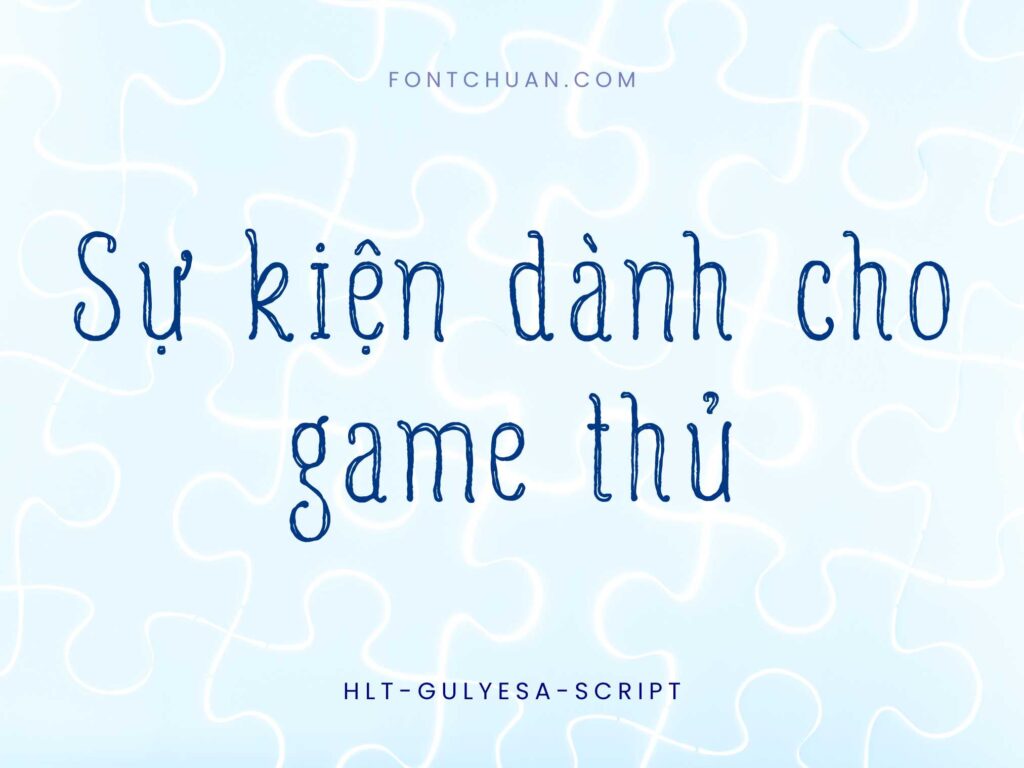
Font HLT Gulyesa Script Việt Hóa
Gulyesa Script là một kiểu chữ viết tay tinh tế, được thiết kế bởi Gülşah Cansever. Phông chữ này mang phong cách thư pháp hiện đại, với các đường nét mềm mại và uyển chuyển, tạo nên sự thanh lịch và cuốn hút cho các thiết kế. Với sự Việt hóa của HLT, Gulyesa Script hỗ trợ đầy đủ các ký tự tiếng Việt, giúp người dùng dễ dàng áp dụng trong các dự án đa ngôn ngữ. Thành viên của Font Chuẩn đã sưu tầm và chia sẻ phông chữ này nhằm đáp ứng nhu cầu đa dạng của cộng đồng thiết kế.
Về đặc điểm thiết kế, Gulyesa Script sở hữu các ký tự được thiết kế tỉ mỉ, mang lại cảm giác nhẹ nhàng và sang trọng. Phông chữ này đặc biệt phù hợp cho các dự án như thiệp mời, bìa sách, poster, logo và các ấn phẩm quảng cáo, nơi cần sự tinh tế và ấn tượng mạnh mẽ. Ngoài ra, Gulyesa Script cũng thích hợp cho các sự kiện như lễ hội, sinh nhật, Valentine và Trung thu, mang lại không khí ấm áp và lãng mạn. Trong lĩnh vực ngành nghề, phông chữ này được ứng dụng rộng rãi trong quảng cáo, thiết kế thiệp cưới, giáo dục và công nghệ, góp phần tạo nên sự độc đáo và thu hút cho các sản phẩm và thương hiệu.